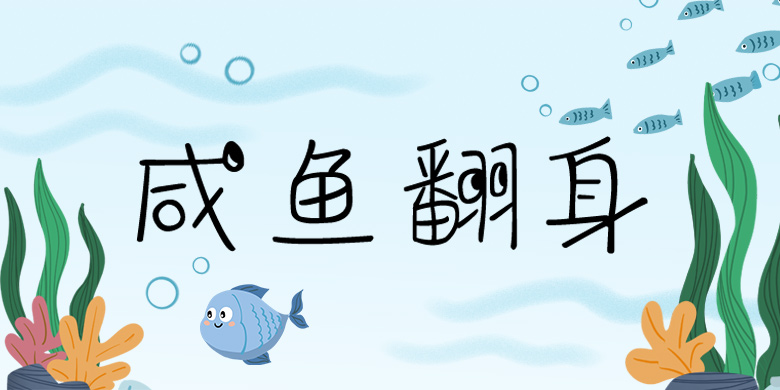
品牌:方正手迹设计师:郑红发行时间:2018字库编码:大陆简体(GB2312-80)分类:创意书写字体属性:精品字
这一款具有卡通元素的创意类手写字体,充满稚气的字形,稳中有变的笔画,转折处恰到好处的圆角处理,都使得基础字形有良好的辨识性。鱼元素的加入,完整的阐述了咸鱼这一主题。适用于少年儿童类的书刊、品牌广告和产品包装设计,以及社交网络的个性化用字。